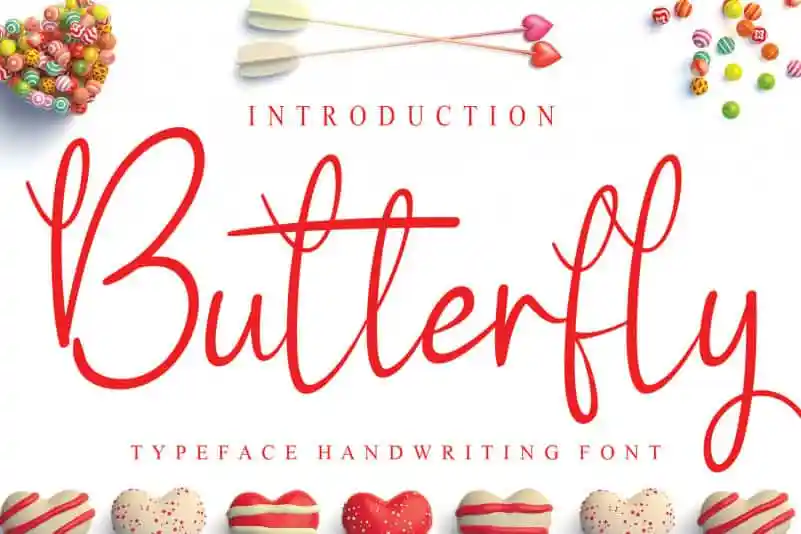
Butterfly1 Script Font
A Butterfly1 Script Font é uma fonte criada por Designer CreativeLetter, ideal para quem busca uma experiência única no design de texto. Com seu estilo retrô e elegante, essa fonte é perfeita para qualquer projeto que você esteja desenvolvendo. Ela oferece detalhes profundos e sutis, acentuando o significado das palavras em um nível até então não alcançado. Para quem aprecia algo de novo e sofisticado na escrita digital, essa fonte é uma ótima escolha. Seja para textos legíveis ou criações artísticas, Butterfly1 Script Font é a escolha ideal. Com seu formato handwriting e sutilezas elegantes, você se surpreenderá com o resultado final, tornando cada palavra um verdadeiro trabalho de arte.